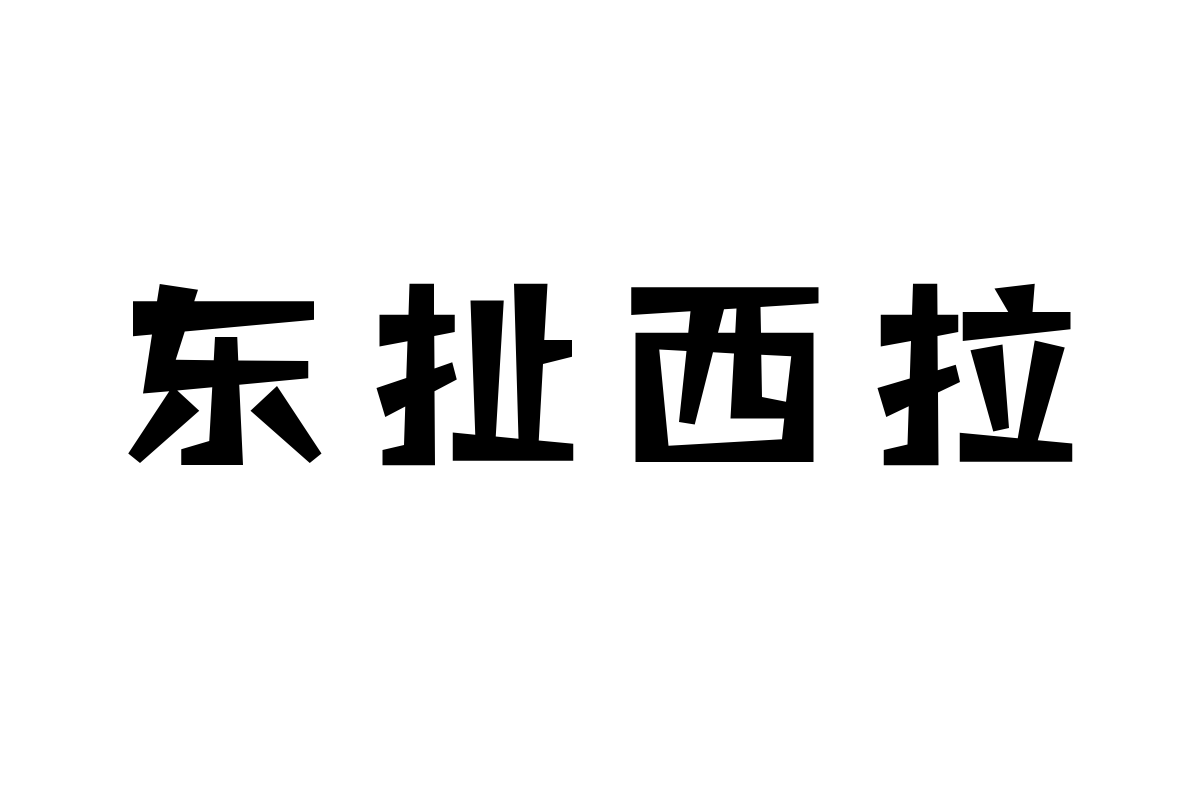
汉仪趣黑简是一款具有现代感的中文简体字体,其特点是字形简洁、线条流畅,给人一种轻松愉悦的感觉。这款字体适用于各种印刷品和数字媒体,如书籍、杂志、报纸、广告、网页等。
汉仪趣黑简采用了现代设计手法,将传统汉字的笔画进行了简化和优化,使其更加符合现代人的审美习惯。同时,该字体还保留了一些传统的书法韵味,使得整体风格既有现代感又不失文化底蕴。
在实际应用中,汉仪趣黑简可以很好地适应不同场景的需求。无论是用于印刷品还是数字媒体,它都能展现出良好的视觉效果和可读性。此外,由于其简洁的字形和流畅的线条,也使得它在设计时更加灵活多变,能够更好地表达设计师的创作意图。
总之,汉仪趣黑简是一款非常适合现代设计的中文简体字体,无论是在印刷品还是数字媒体上都能表现出色。